Font chữ thư pháp được sử dụng phổ biến cho các tác phẩm thiết kế và trình bày văn học. Dù là làm thiệp Tết, thiết kế cho mạng xã hội hay soạn thảo văn bản nghệ thuật, một phông chữ thư pháp phù hợp sẽ tạo ra sự khác biệt lớn.
Font chữ thư pháp là gì?
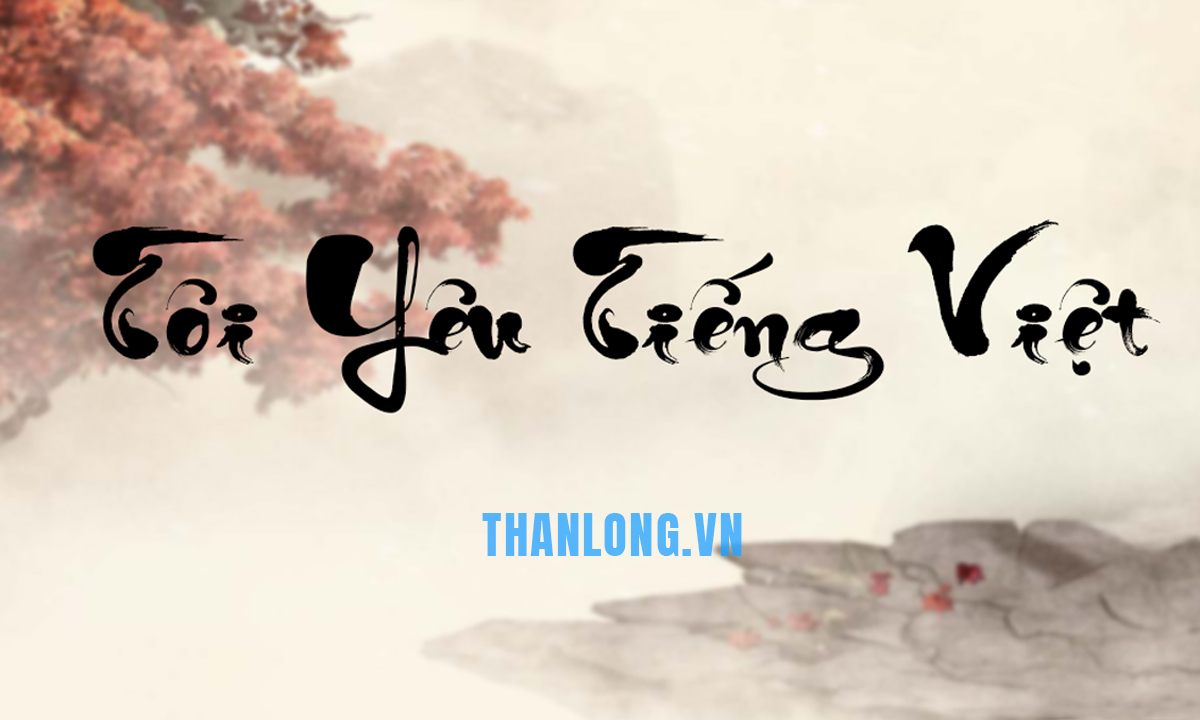
Font chữ thư pháp là bộ phông chữ được thiết kế mô phỏng theo nét bút lông hoặc bút viết tay nghệ thuật. Đặc điểm của nó là những nét thanh, nét đậm uyển chuyển, mềm mại như “phượng múa rồng bay”.
Do tính nghệ thuật cao, loại font này không phù hợp cho các đoạn văn bản dài cần đọc nhanh. Thay vào đó, nó được dùng để tạo điểm nhấn cho các tác phẩm cần tính thẩm mỹ như tiêu đề, logo, thiệp mời, câu đối, trích dẫn hay…
Hiện nay, phông chữ thư pháp có rất nhiều kiểu chữ đa dạng và độc đáo. Người sử dụng có thể những loại font thư pháp đẹp để hiện thị và mô tả.
Những đặc điểm nổi bật của font chữ thư pháp
Bộ phông chữ thư pháp được yêu thích nhờ sở hữu nhiều ưu điểm độc đáo, giúp các thiết kế của bạn trở nên khác biệt và có hồn hơn:
- Tính nghệ thuật và cảm xúc cao: Mỗi phông chữ thư pháp đẹp đều mô phỏng nét bút uyển chuyển, gợi cảm giác hoài cổ và sang trọng. Chúng giúp truyền tải thông điệp một cách tinh tế, có hồn hơn so với các font chữ thông thường.
- Đa dạng phong cách, tạo dấu ấn riêng: Có hàng ngàn các font chữ thư pháp khác nhau, từ phong cách ông đồ cổ điển đến font chữ thư pháp hiện đại. Sự đa dạng này giúp bạn dễ dàng tạo ra các thiết kế độc đáo và mang đậm dấu ấn cá nhân.
- Hỗ trợ tiếng Việt có dấu: Hầu hết các bộ font được chia sẻ hiện nay đều là font chữ thư pháp Việt hóa, đảm bảo bạn có thể gõ tiếng Việt có dấu một cách đầy đủ và chính xác mà không bị lỗi font.
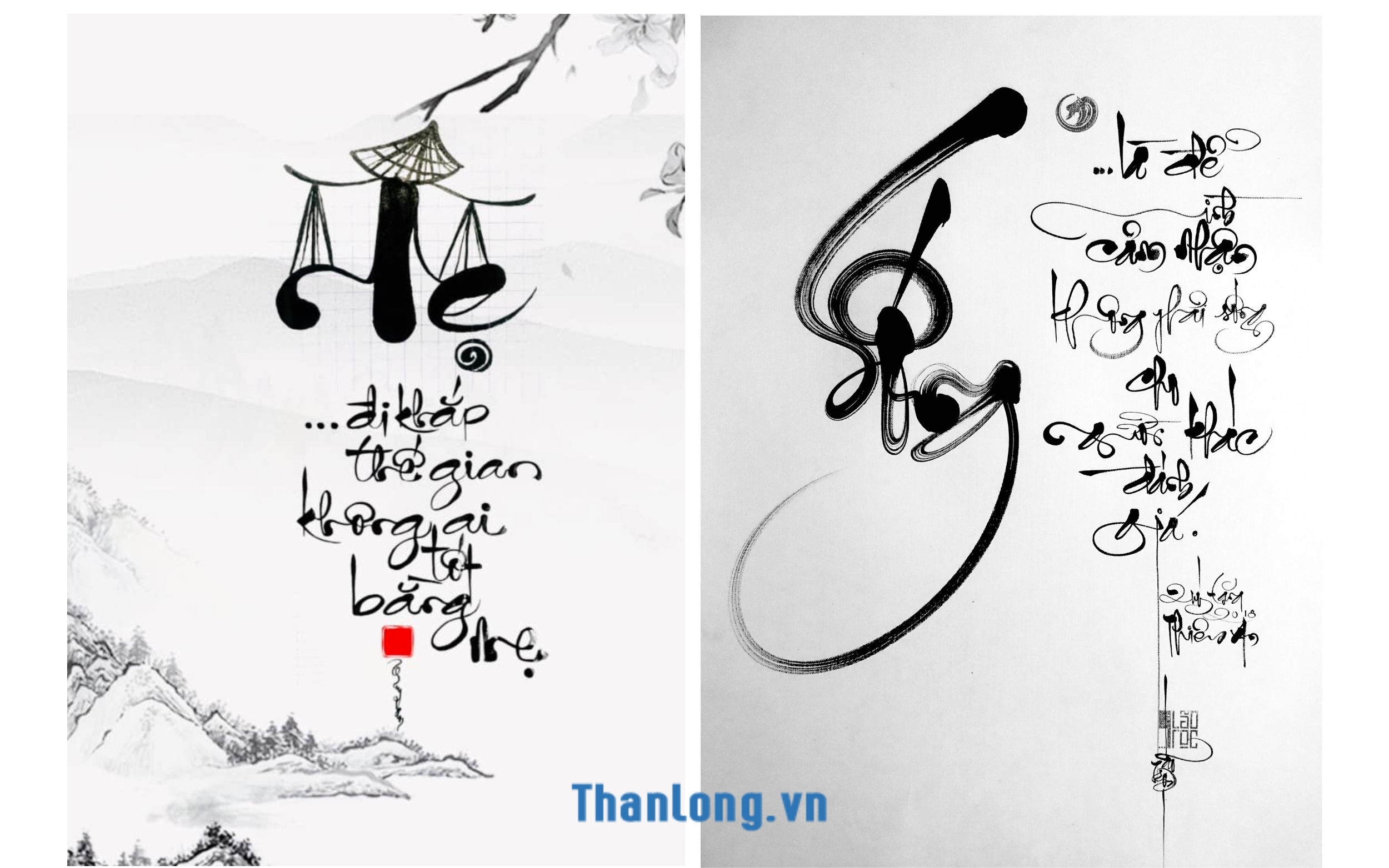
Các kiểu chữ thư pháp phổ biến hiện nay
Thế giới font chữ thư pháp tiếng Việt vô cùng đa dạng. Người dùng có thể lựa chọn nhiều loại font khác nhau và phù hợp. Dưới đây sẽ là một số phông thư pháp đã việt hóa được nhiều người sử dụng:
Font chữ thư pháp Cổ điển (Ông Đồ, Tết)
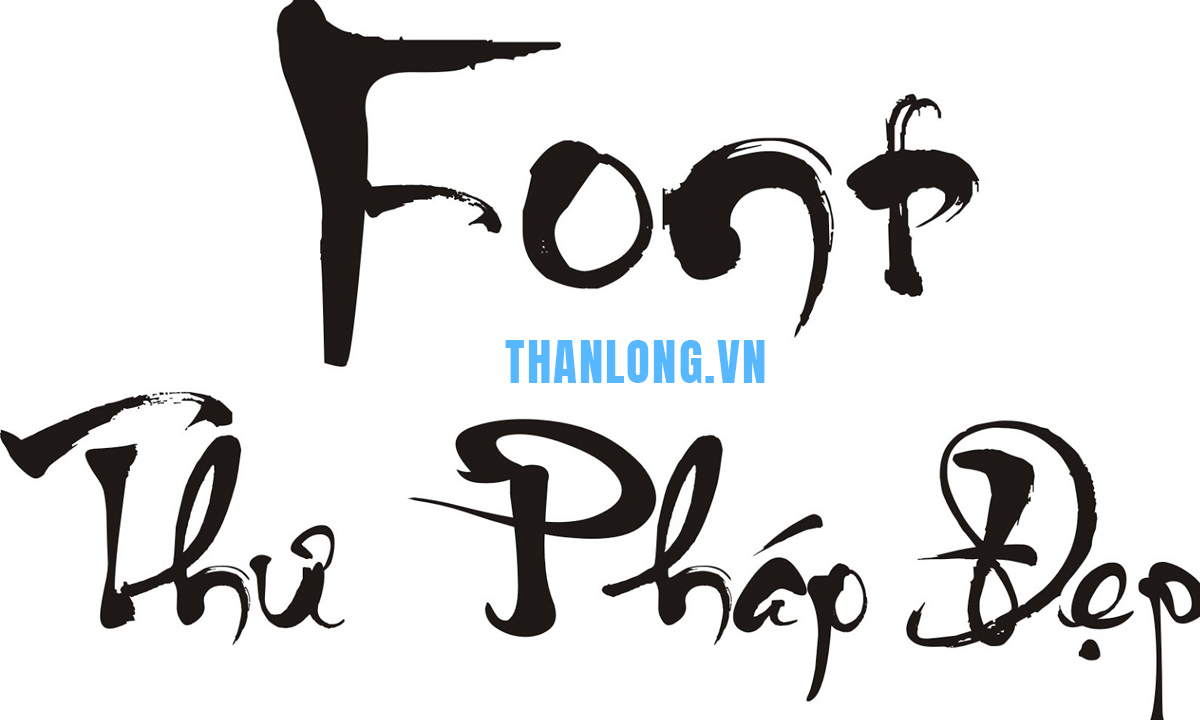
Phong cách này mang đậm nét trang trọng, hoài cổ, lấy cảm hứng từ nghệ thuật thư pháp Hán Nôm và font chữ thư pháp Trung Quốc. Các đường nét của font thường dứt khoát, mô phỏng theo lối viết của các bậc thầy xưa.
Đây chính là font chữ thư pháp Tết hay font chữ thư pháp ông đồ mà bạn thường thấy trong các ấn phẩm dịp Tết Nguyên Đán. Nó gợi lên không khí sum vầy và truyền thống. Nó không chỉ dùng để trang trí, mà còn để truyền tải những giá trị văn hóa lâu đời.
Ứng dụng phổ biến:
- Viết câu đối, thiệp chúc mừng năm mới.
- Thiết kế bao lì xì, lịch Tết, các ấn phẩm văn hóa.
- Trang trí trong không gian thờ cúng, từ đường.
- Thể hiện các chữ mang ý nghĩa đặc biệt: Phúc, Lộc, Thọ, Tâm, An, Nhẫn…
Font chữ thư pháp xuân
Đúng như tên gọi, font chữ thư pháp xuân được sinh ra để lan tỏa không khí vui tươi, rộn ràng của những ngày Tết Nguyên Đán.
Nét chữ của phong cách này thường bay bổng, phóng khoáng và tràn đầy năng lượng, tượng trưng cho một sự khởi đầu mới đầy hy vọng. Nó không chỉ là một phông chữ, mà còn là một phần không thể thiếu trong văn hóa ngày Tết của người Việt.
Ứng dụng chính của font thư pháp xuân:
- Viết câu đối Tết, các lời chúc mừng năm mới.
- Thiết kế bao lì xì, thiệp chúc Tết, lịch treo tường.
- Trang trí cho các banner, poster sự kiện Tất niên và Chào Xuân.
- Tạo điểm nhấn cho các ấn phẩm văn hóa mang chủ đề mùa xuân.
Font chữ thư pháp Viết tay (Bút lông)
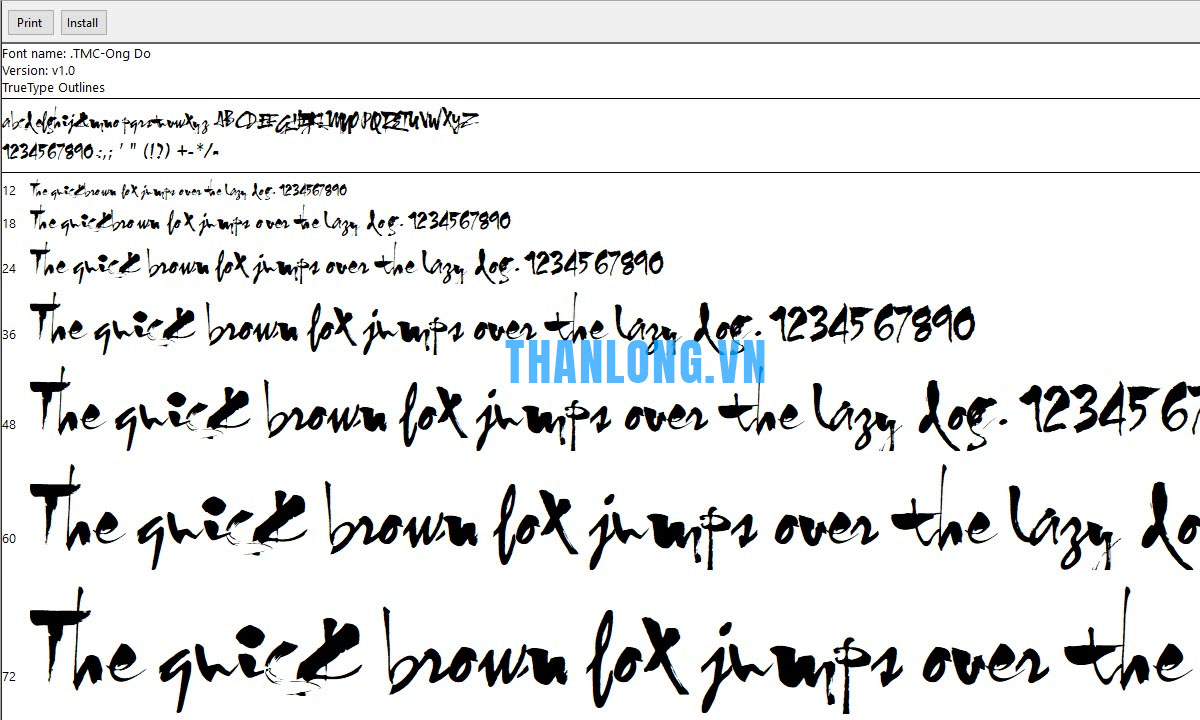
Đây là phong cách được yêu thích và sử dụng rộng rãi nhất vì tính đa dụng của nó. Các font chữ thư pháp bút lông mô phỏng chân thực từng nét mực uyển chuyển, thanh thoát, tạo cảm giác tự nhiên, mềm mại và gần gũi.
Điểm mạnh của phong cách này là sự cân bằng hoàn hảo giữa tính nghệ thuật và sự dễ đọc. Nó không quá cách điệu như font cổ điển, giúp người xem dễ dàng nắm bắt nội dung mà vẫn cảm nhận được vẻ đẹp tinh tế.
Phù hợp cho các thiết kế:
- Thiết kế logo thương hiệu, slogan cần sự mềm mại.
- Làm thiệp mời (đặc biệt là thiệp cưới), thư cảm ơn.
- Tạo các bài đăng trích dẫn (quotes) trên mạng xã hội.
- Trang trí bao bì sản phẩm cần sự sang trọng, tinh tế.